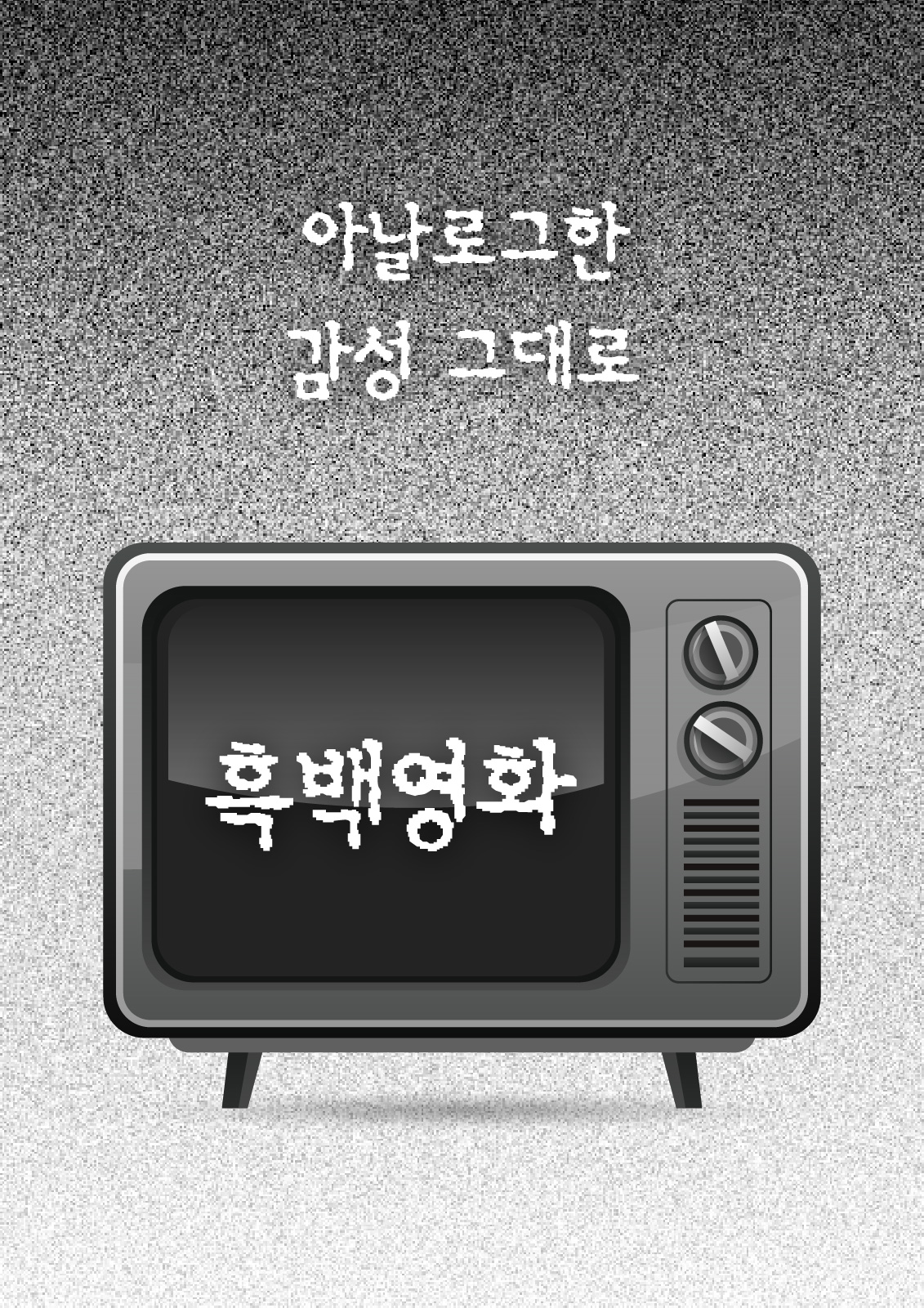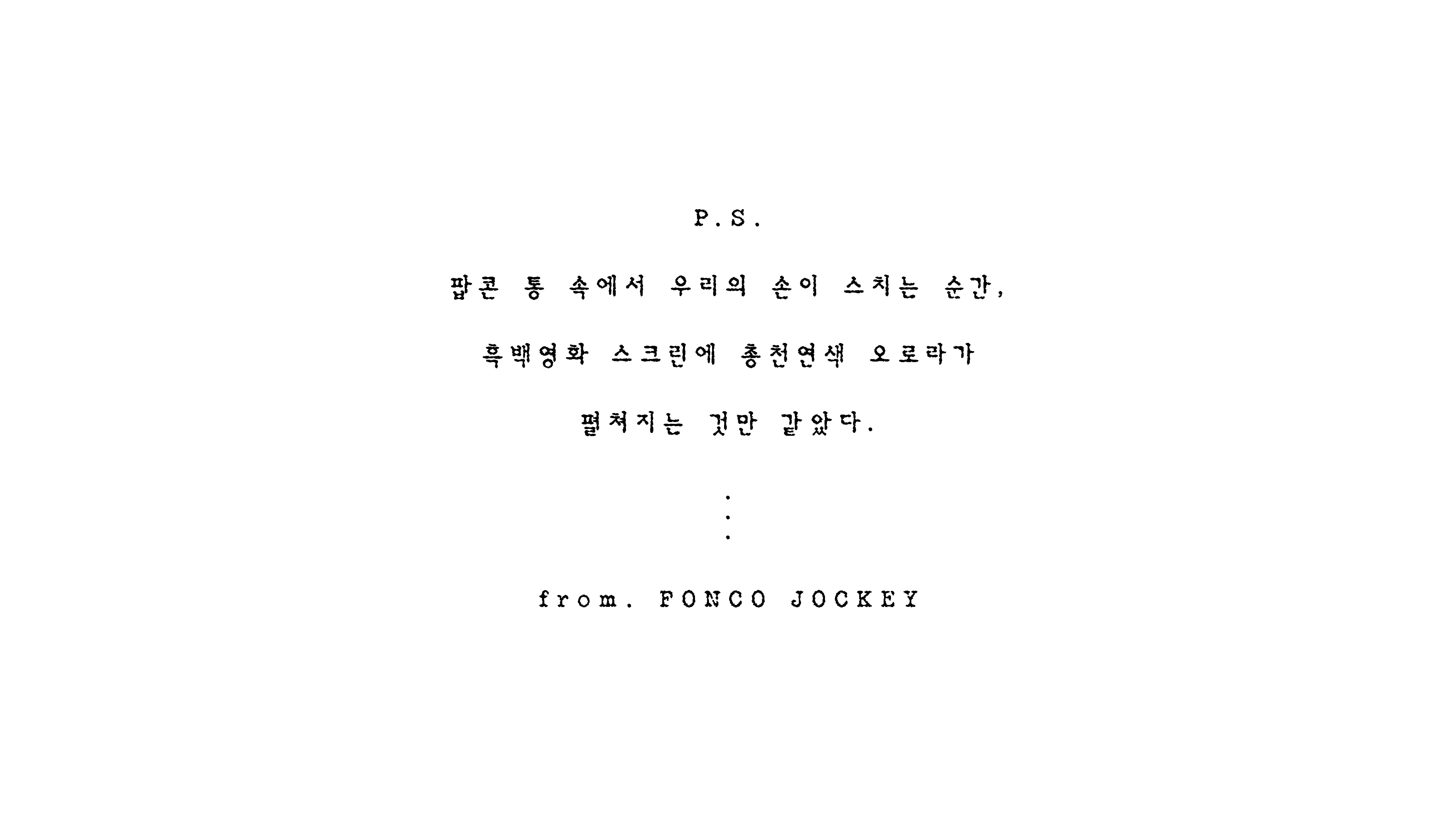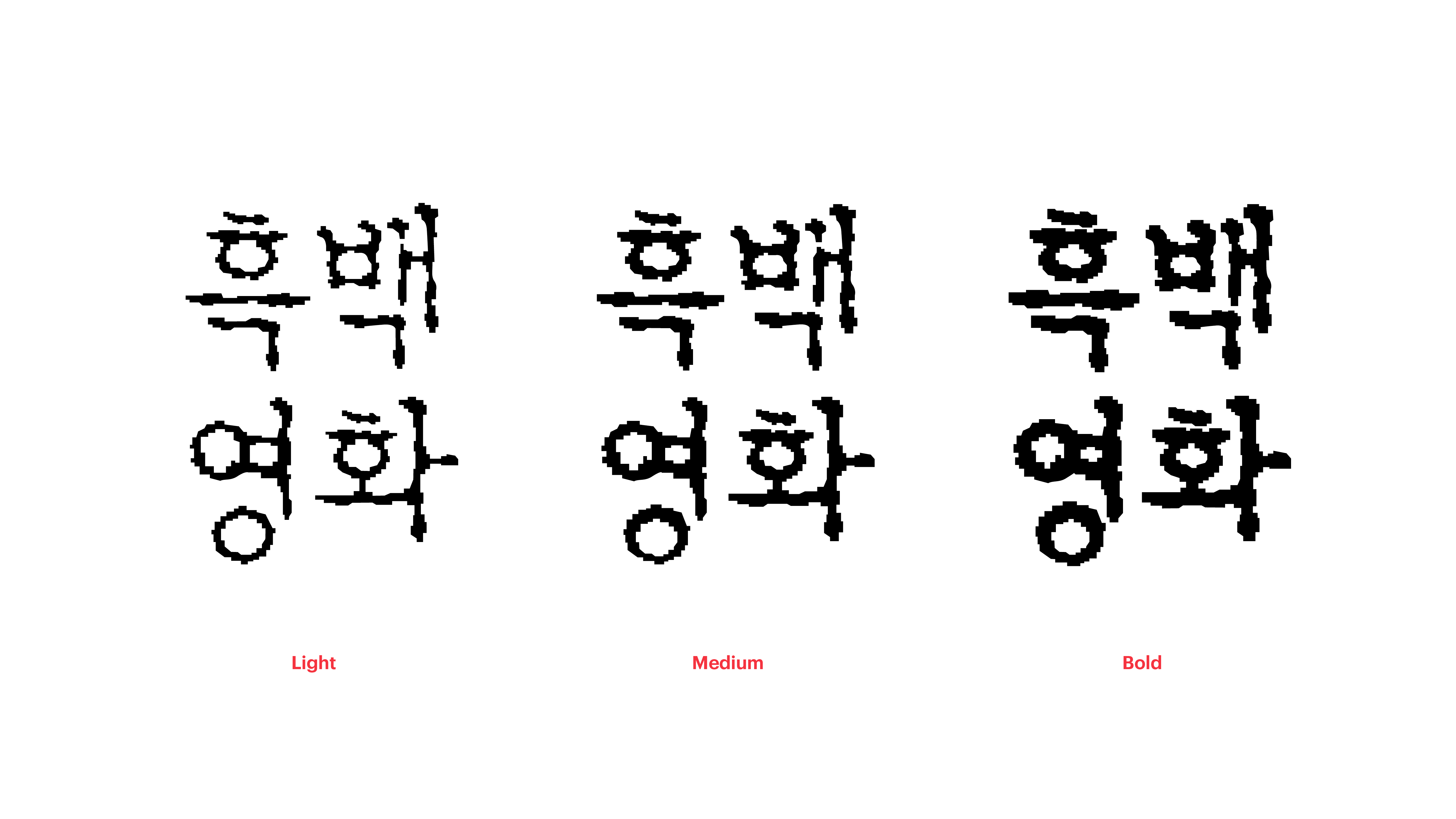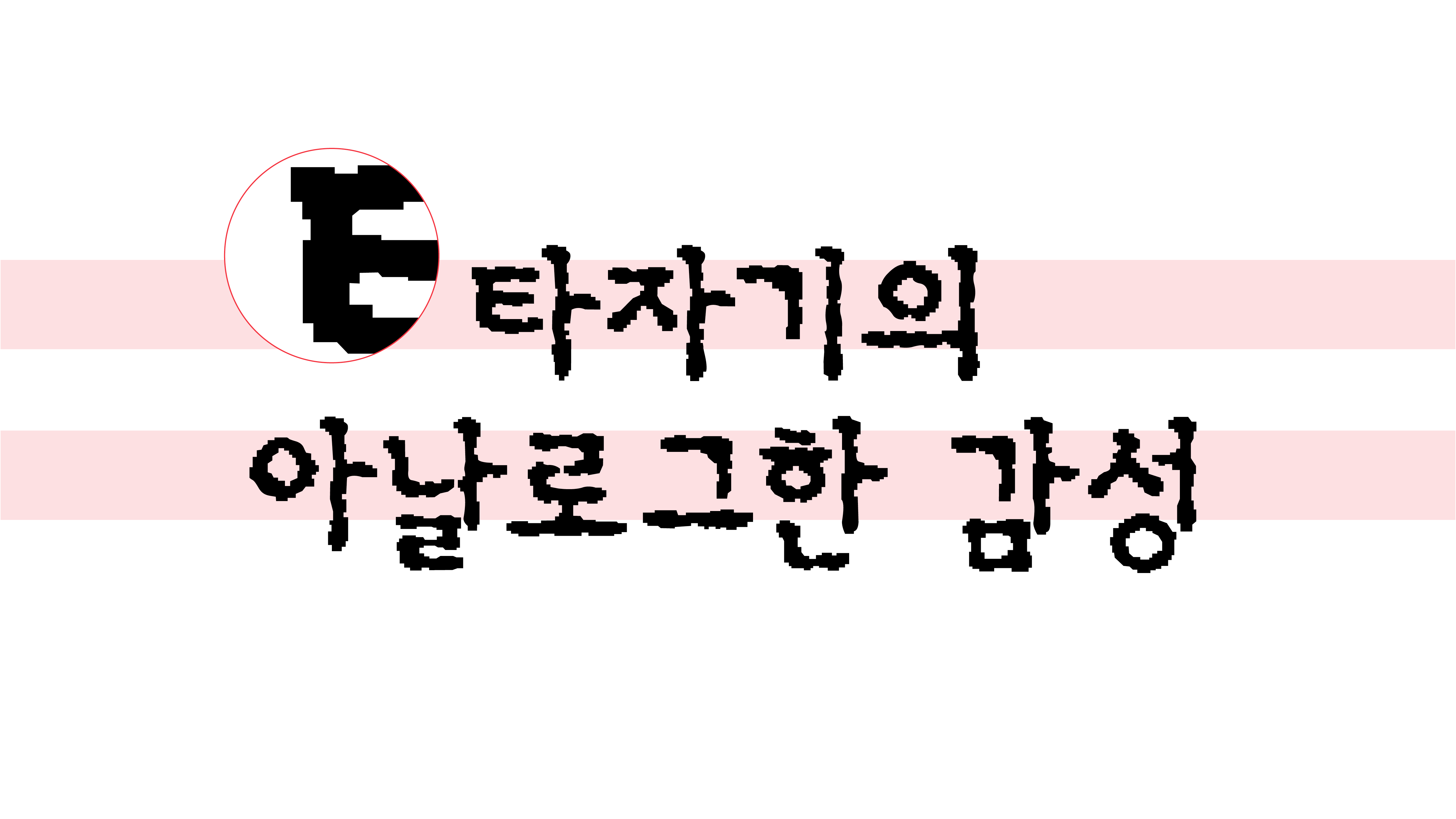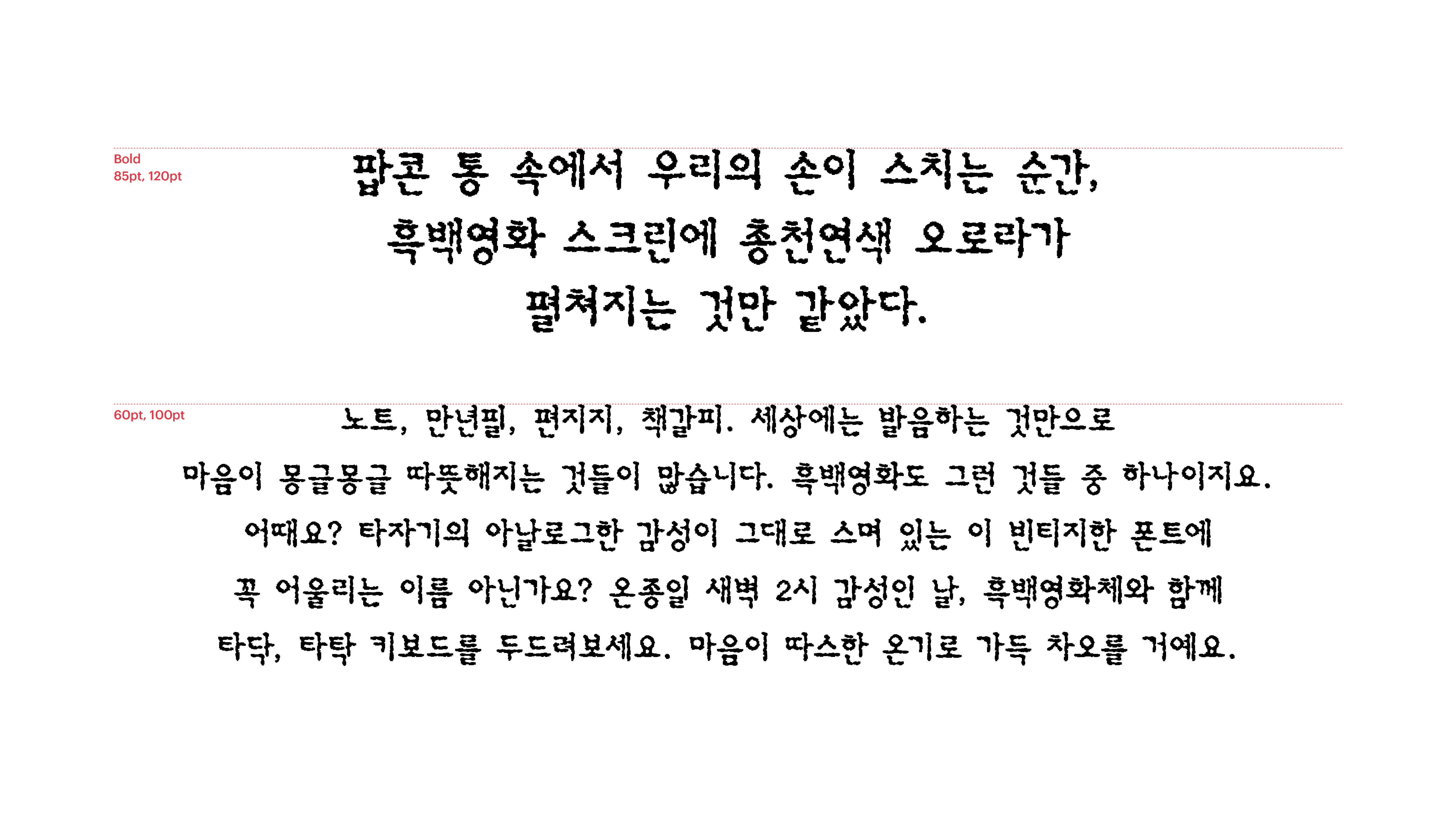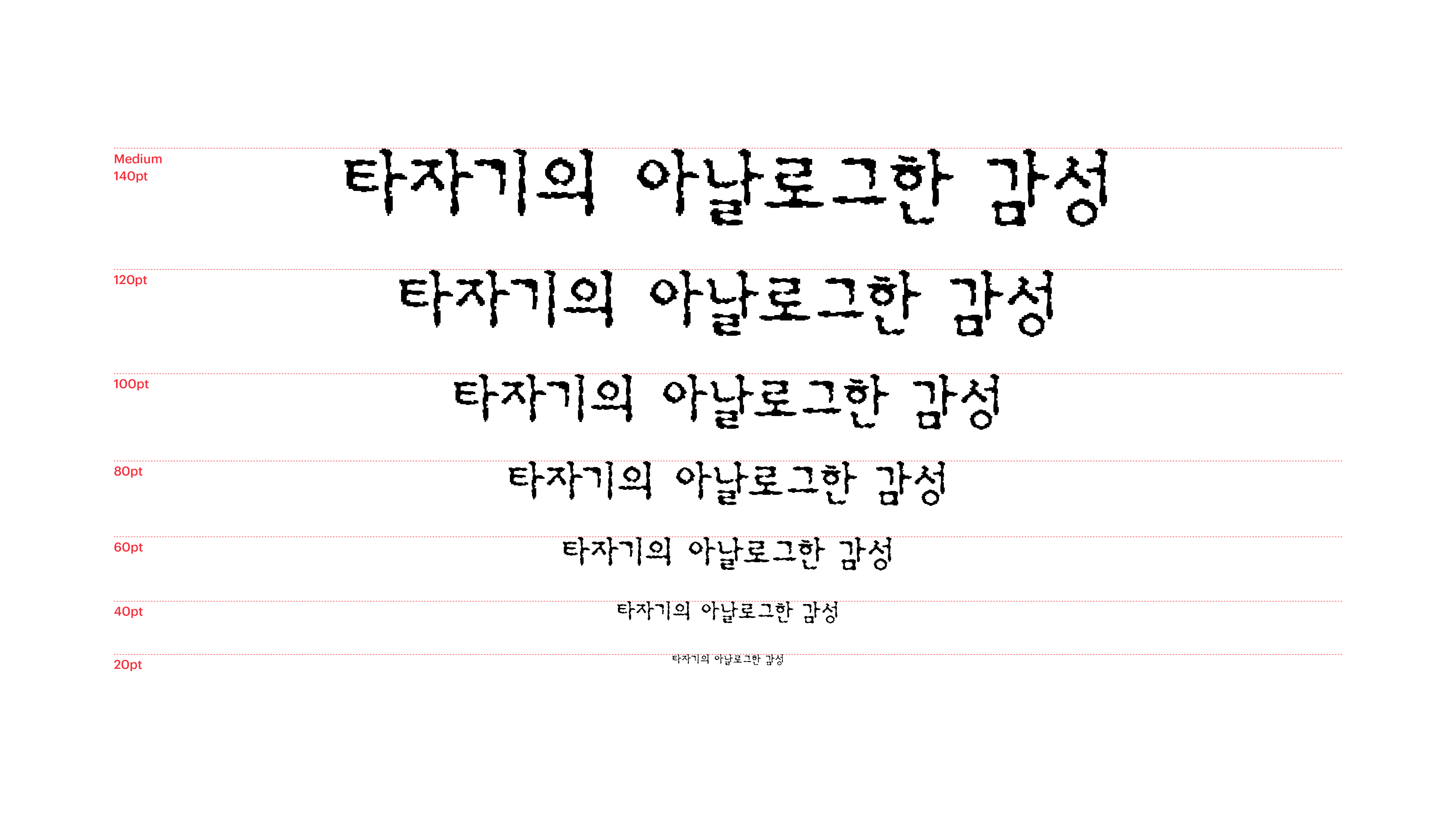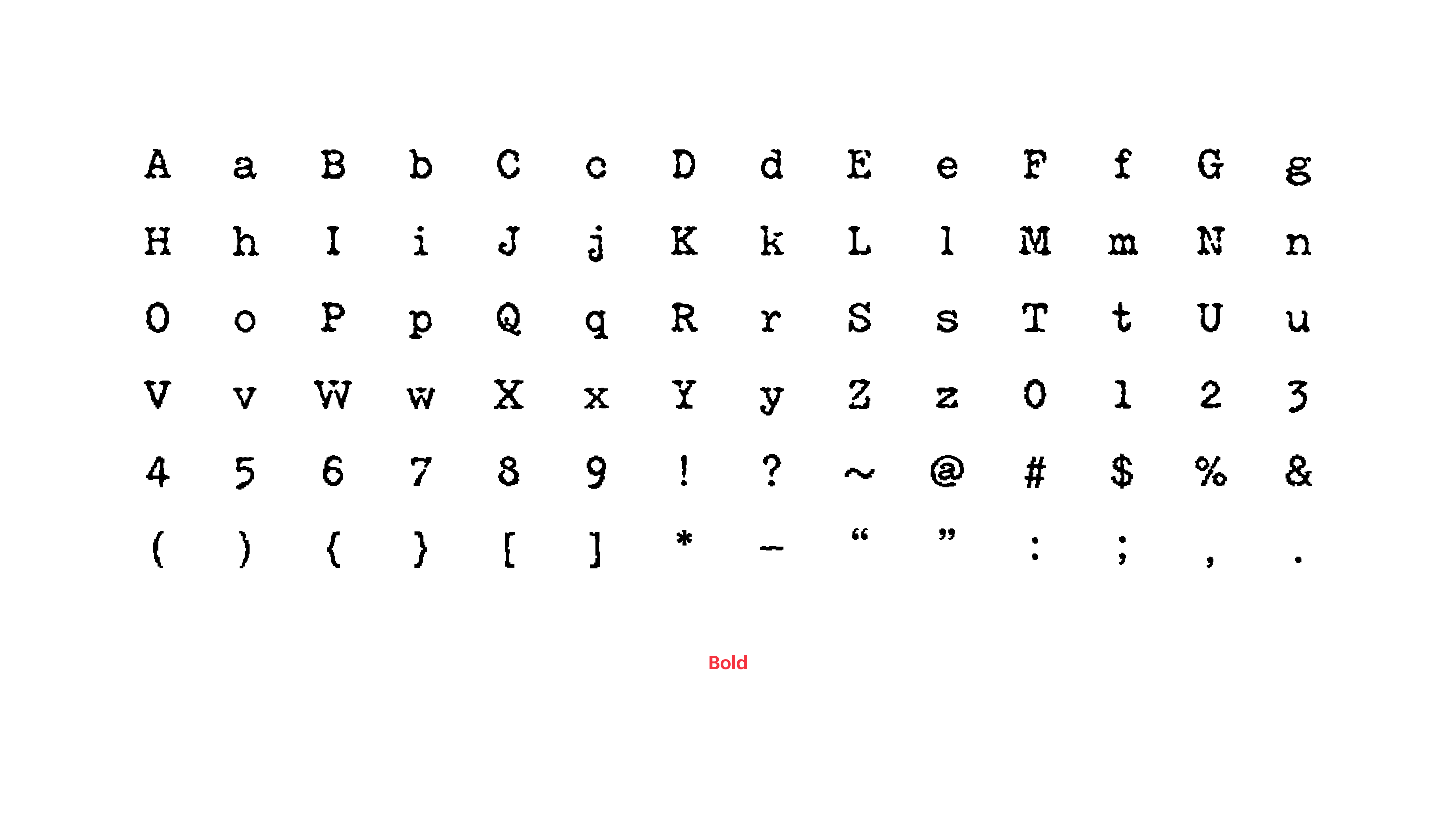
노트, 만년필, 편지지, 책갈피. 세상에는 발음하는 것만으로 마음이 몽글몽글 따뜻해지는 것들이 많습니다. 흑백영화도 그런 것들 중 하나이지요. 어때요? 타자기의 아날로그 한 감성이 그대로 스며 있는 이 감성적인 폰트에 꼭 어울리는 이름 아닌가요? 하루 종일 새벽 2시 감성인 날, 흑백영화체와 함께 타닥, 타탁 키보드를 두드려보세요. 마음이 따스한 온기로 가득 차오를 거예요.
Yoon 흑백영화